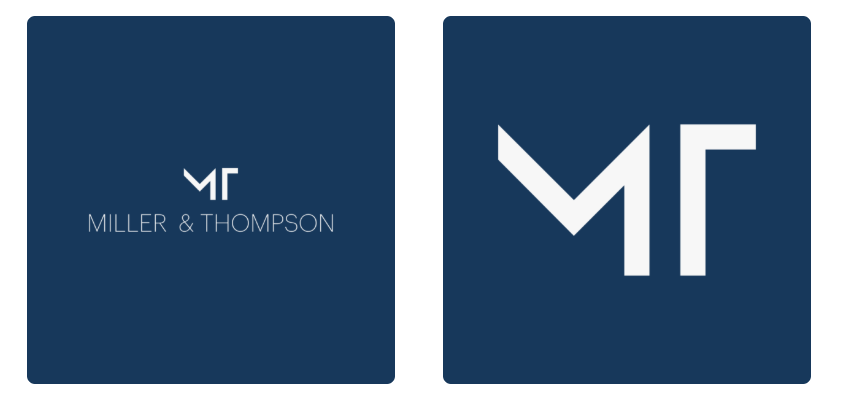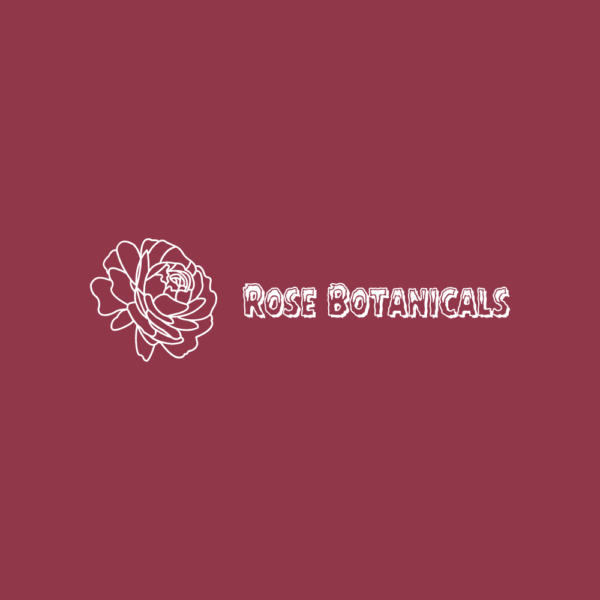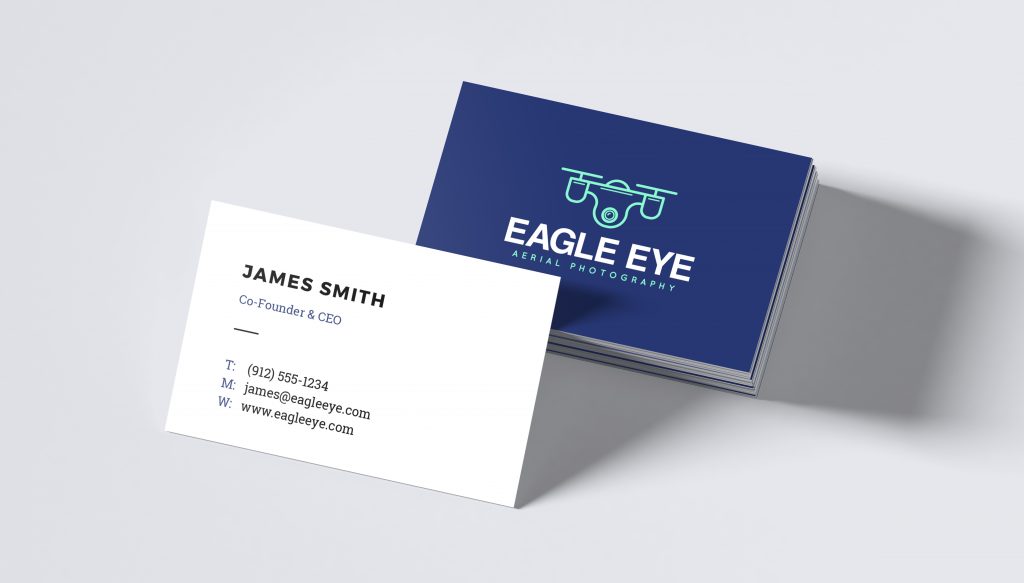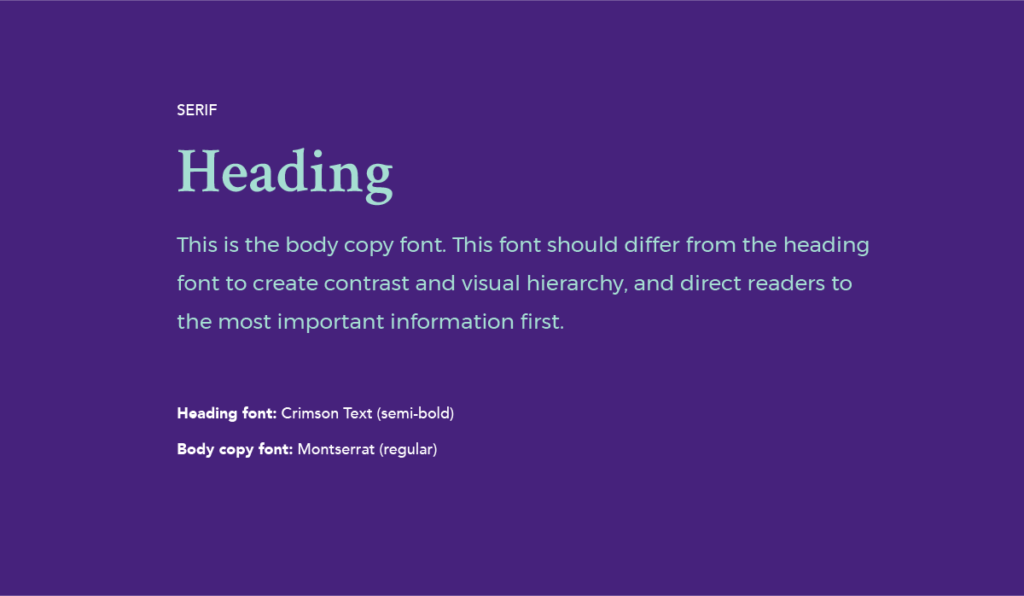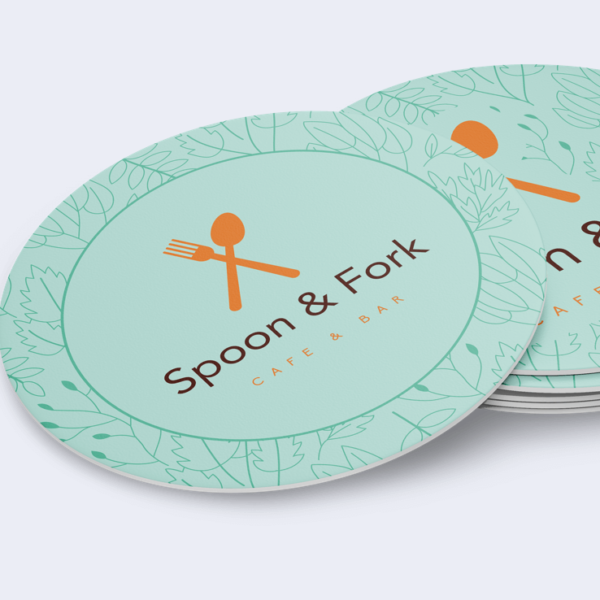
5 lời khuyên khi chọn và sử dụng font chữ thiết kế logo
Font chữ thiết kế logo không chỉ là tên của một công ty, mà nó còn truyền đạt một cảm giác về phong cách và tính cách của thương hiệu; có tác động trực tiếp đến suy nghĩ và cảm xúc của người tiêu dùng. Chính vì vậy, cần lưu ý tới một số điều dưới đây khi chọn và sử dụng font chữ.
5 lời khuyên khi chọn và sử dụng font chữ thiết kế logo
1. Ưu tiên mức độ dễ đọc
Tính dễ đọc là điều bạn phải luôn cân nhắc khi thiết kế logo. Có rất nhiều yếu tố quyết định để tạo ra một logo dễ đọc mà vẫn truyền đạt được bản sắc thương hiệu của bạn. Bạn muốn một sự cân bằng giữa văn bản có thể đọc được, nhưng cũng có một cái gì đó đáng nhớ và độc đáo cho thương hiệu của bạn! Dưới đây là một số lời khuyên về mức độ dễ đọc:
• Sự kết hợp màu sắc là rất quan trọng. Đọc văn bản màu sáng trên nền sáng làm cho logo của bạn rất khó đọc. Lựa chọn không cho màu sắc tạo ra độ tương phản.
• Font chữ dày có thể khó đọc trong khi font chữ script cần rất nhiều khoảng trống xung quanh, vì vậy, hãy xem xét tới việc tăng khoảng cách giữa các chữ cái và chiều cao dòng (khoảng cách giữa các dòng văn bản). Và tốt hơn hết nên tránh tất cả các mũ bằng mọi giá với font chữ script!
• Xem lại những điều quan trọng trong hệ thống phân cấp thị giác để cảm nhận về cách sử dụng căn chỉnh, không gian, màu sắc và kích thước một cách hiệu quả nhất trong logo.
2. Ghép một font chữ thiết kế logo mỏng với một biểu tượng hoặc chữ lồng
Chúng tôi biết bạn thích font chữ thiết kế logo mỏng: Thanh lịch và tối giản, trong khi chúng có thể là xu hướng, font chữ thiết kế logo mỏng vẫn nhận được nhiều sự chú ý cho cảm giác cổ điển của chúng. Nếu bạn đang sử dụng một font chữ thiết kế logo mỏng, chúng tôi có một số khuyến nghị.
Font chữ thiết kế logo mỏng luôn không thường xuyên xuất hiện trong bản in và chúng không hiển thị tuyệt vời trên phương tiện truyền thông xã hội khi thu nhỏ vào hình ảnh hồ sơ của bạn. Chúng tuyệt vời trên các trang web và tài sản kỹ thuật số khi không gian cho chúng khá lớn.
font-chu-thiet-ke-logo-bee-art-01Ví dụ về sự hiển thị của font chữ thiết kế logo mỏng
Nếu bạn muốn sử dụng một font chữ thiết kế logo mỏng trong logo của mình, chúng tôi khuyên bạn nên ghép nó với một biểu tượng hoặc chữ lồng. Bằng cách đó, ở những nơi font chữ mỏng không hiển thị tốt (ví dụ như hình đại diện), bạn có tùy chọn sử dụng chữ lồng hoặc biểu tượng của mình! Xem mức độ ảnh hưởng và mức độ rõ ràng của chữ lồng bên phải là ảnh đại diện trên mạng xã hội? Trong khi đó logo bên trái hầu như không nhìn thấy được.
3. Font chữ thiết kế logo rất chi tiết không giảm quy mô xuống
Chúng tôi yêu thích font chữ với cá tính. Sự độc đáo của chúng sẽ giúp làm cho thương hiệu của bạn nổi bật và được ghi nhớ.
font-chu-thiet-ke-logo-bee-art-01Ví dụ về font chữ thiết kế logo cá tính
Với những không gian như nhỏ hơn như ảnh đại diện, tiêu đề thư và favicon sẽ không thể hiện chi tiết trong font chữ và tính cách của nó sẽ bị mất. Tệ hơn nữa, bạn có khả năng làm giảm mức độ dễ đọc của logo của bạn và đó là một điều không nên!
Một lần nữa, chúng tôi khuyên bạn nên ghép một font chữ thiết kế logo chi tiết với một chữ lồng hoặc ký hiệu hoặc chỉ sử dụng chúng nếu bạn dự định đặt nó trên những không gian lớn như cửa sổ cửa hàng, túi vải, máy bay, decal dán tường, v.v.
4. Sử dụng các font chữ thiết kế logo khác nhau cho tên công ty và slogan của bạn
Slogan logo của bạn là một cơ hội để nói với người tiêu dùng thêm một chút về công ty của bạn. Cho dù điều đó giải thích những gì bạn làm, hoặc bạn đã kinh doanh được bao lâu, bạn muốn khẩu hiệu của mình nổi bật và font chữ logo của bạn không làm mất đi sự tập trung vào nó?
font-chu-thiet-ke-logo-bee-art-03Ví dụ về việc sử dụng các font chữ thiết kế logo khác nhau cho công ty và slodan trên danh thiếp
Lời khuyên tốt nhất của chúng tôi ở đây là ghép các font chữ logo và slogan của bạn một cách cẩn thận. Bằng cách chiến lược chọn một cặp font chữ phối hợp tốt với nhau, bạn sẽ có thể đạt được sự quan tâm, dễ đọc, cân bằng, phân cấp thị giác và độ tương phản trong thương hiệu của bạn tốt hơn.
Một số lựa chọn ghép font chữ điển hình mà chúng tôi khuyên là:
• Văn bản logo Serif + khẩu hiệu sans-serif
• Font chữ viết tay hoặc chữ viết logo + sans-serif
• Font chữ logo hiện đại + slogan slab-serif
• Font chữ logo vui nhộn + khẩu hiệu sans-serif
font-chu-thiet-ke-logo-bee-art-04Ví dụ về việc sử dụng các font chữ thiết kế logo khác nhau cho công ty và slodan trên danh thiếp
5. Giữ cho font chữ thiết kế logo đơn giản
Logo cần sự linh hoạt. Chúng thường được in trên nhiều loại không gian khác nhau, được tăng hoặc giảm, được yêu cầu ở định dạng đen trắng. Nếu logo của bạn quá phức tạp, sử dụng đồng thời nhiều font chữ trong cùng một không gian thiết kế, bao gồm cả một biểu tượng đi kèm, sẽ làm cho nó trở nên lộn xộn. Và con người có một sự bảo vệ tuyệt vời chống lại sự lộn xộn chính là chặn hầu hết mọi thứ.